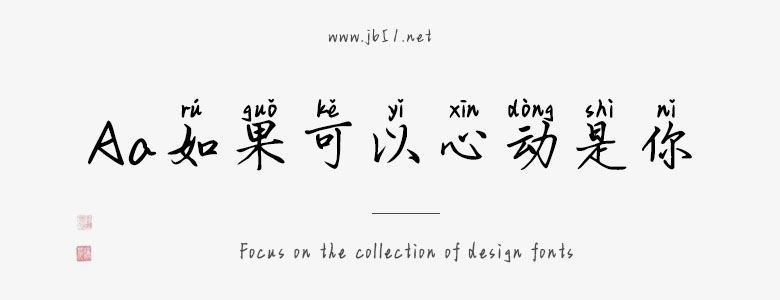
Aa如果可以心動(dòng)是你是Aa字庫(kù)推出的藝術(shù)字體,字體筆觸適中,字形端正 ,具有很好的視覺(jué)感,適合應(yīng)用于藝術(shù)設(shè)計(jì)、平面宣傳設(shè)計(jì)、網(wǎng)頁(yè)設(shè)計(jì),書(shū)法字帖等領(lǐng)域,歡迎需要的朋友下載使用。